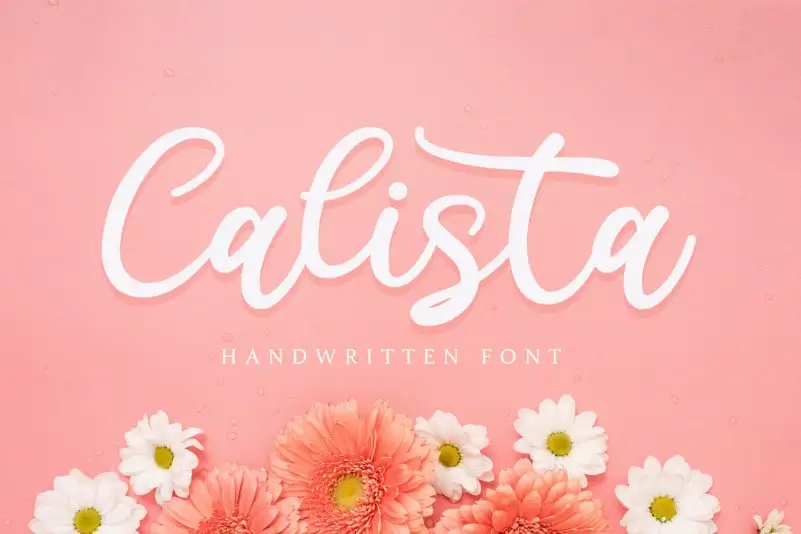
Calista – Handwritten Font – Download Grátis
A Calista – Handwritten Font é uma nova face de tipo escrita a mão que traz beleza inigualável para diversos tipos de design. Ideal para invições de casamento, cartões de agradecimento, frases, cartas de bem-vindo, logotipos, identidades de marca, designs de móveis de casa, embalagens de produto, xícaras, postais, cartões de agradecimento, rótulos, fotografias e até mesmo água-marinha para eventos especiais. Esta fonte de escrita a mão é um toque que enriquece qualquer projeto gráfico, seja ele uma simples etiqueta ou uma capa de livro sofisticada. Calista não apenas oferece a beleza do estilo a mão, mas também a flexibilidade necessária para adaptar-se a muitos formatos. Perfeito para adicionar um toque único e personalizado a seu design, esta fonte é ideal para todos os amantes de design que buscam uma face de tipo que ressoa com emoções e histórias através de um toque delicado e artesanal. Com Calista, você pode trazer vida à sua arte digital, transformando cada projeto em algo único e memorável.